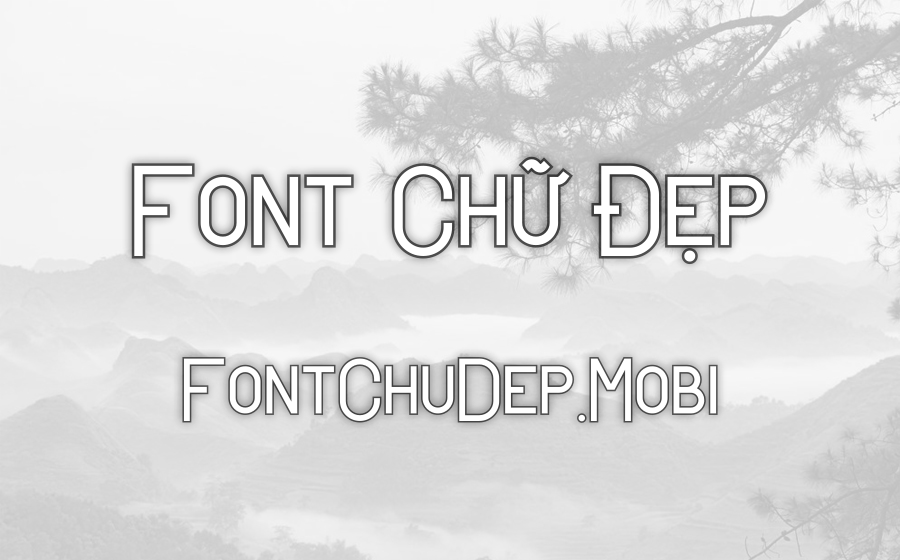
Font VL Cvetanoff Việt Hóa
VL Cvetanoff
VL-Cvetanoff là một kiểu chữ sans-serif hiện đại và đầy sức hút đến từ VPcreativeshop. Được xây dựng với những nét thiết kế đơn giản nhưng tinh tế, phông chữ này mang đến vẻ đẹp chuyên nghiệp cùng sự dễ chịu khi đọc, cực kỳ hữu ích trong các thiết kế. Điều đặc biệt hơn cả, VL-Cvetanoff đã được Việt Linh Việt hóa hoàn toàn, hỗ trợ đầy đủ các ký tự tiếng Việt, giúp người dùng dễ dàng tích hợp vào các dự án sáng tạo mà không gặp trở ngại nào. Được FontChuDep.mobi sưu tầm và chia sẻ rộng rãi, VL-Cvetanoff phục vụ cho mọi nhu cầu thiết kế đa dạng.
Điều khiến tôi thực sự ấn tượng là sự rõ ràng và tính linh hoạt mà VL-Cvetanoff mang lại. Từ việc sử dụng trong các tiêu đề nổi bật, văn bản dài, thiết kế logo đến các ấn phẩm in ấn, phông chữ này đều tỏ ra phù hợp. Trong lĩnh vực tổ chức sự kiện, VL-Cvetanoff là lựa chọn hoàn hảo cho các tấm thiệp, sự kiện văn hóa, hay những lễ hội tưng bừng. Bên cạnh đó, các ngành nghề như quảng cáo, giáo dục và công nghệ cũng có thể tận dụng sức mạnh đầy tiềm năng của phông chữ này. Đây thực sự là một trải nghiệm tuyệt vời cho bất kỳ nhà thiết kế nào.